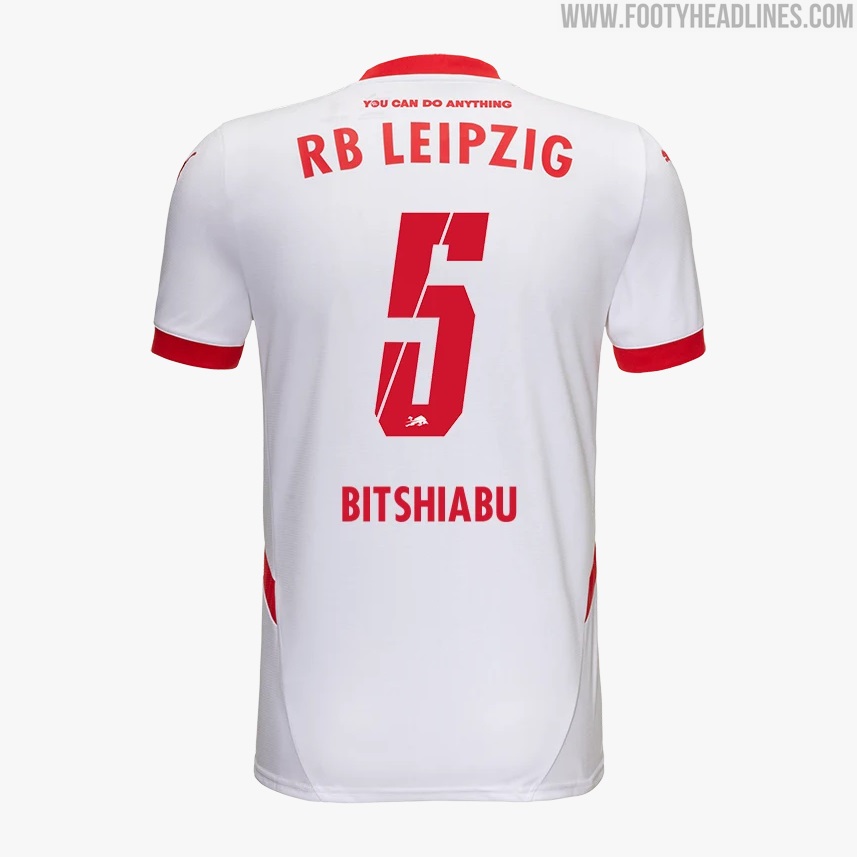
Rilasciato il nuovo font della maglia dell'RB Leipzig 24-25
• Nuova maglia RB Lipsia 24-25: L'RB Lipsia ha presentato la sua nuova maglia per la stagione 24-25, insieme al nuovo font che verrà utilizzato.
• Stile del font: Il nuovo font presenta uno stile classico con caratteri corsivi e una striscia diagonale bianca che attraversa il numero.
Ieri l'RB Lipsia ha presentato la nuova maglia 24-25 e il nuovo font che verrà utilizzato nella stagione 24-25.
Carattere della maglia RB Leipzig 24-25
Il nuovo font della maglia RB Leipzig 24-25 presenta uno stile di numerazione piuttosto classico, con caratteri corsivi e una striscia diagonale bianca che attraversa il numero.